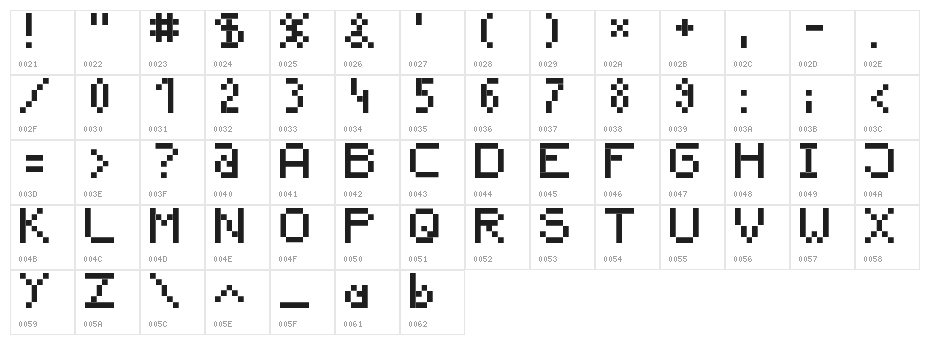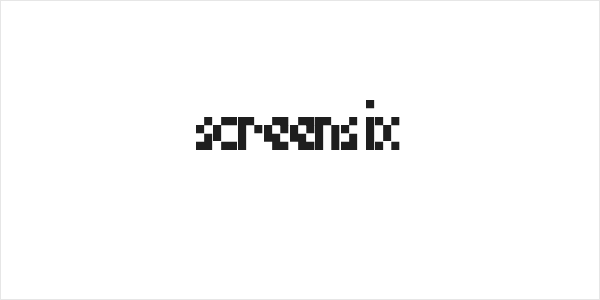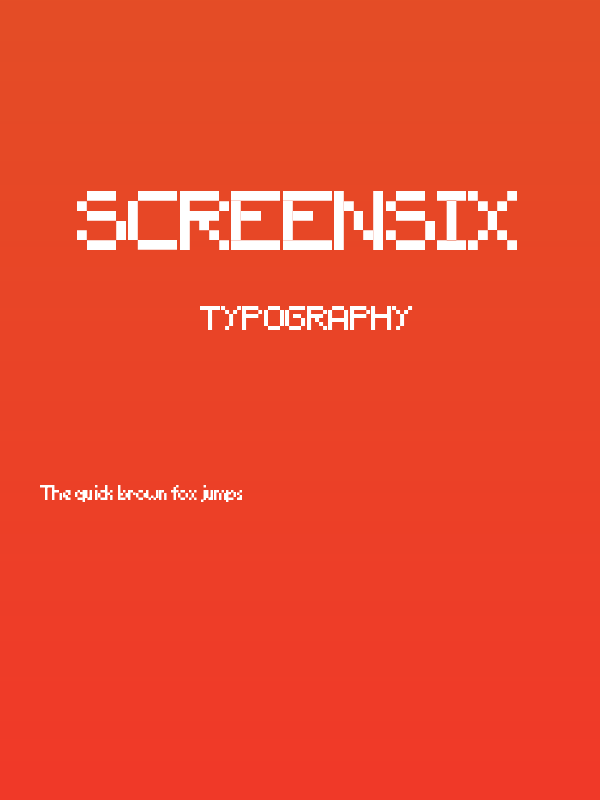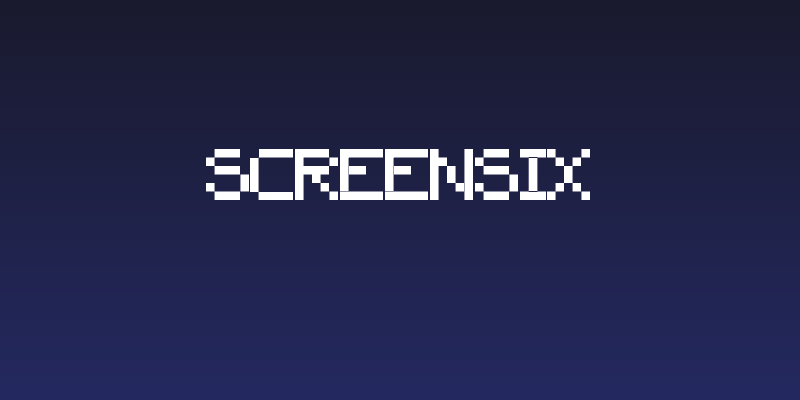
screensix Font
✎ Pixel
| Gesamtstil | Retro, Digital |
| Anwendungsfall | Headlines, Logos, Digital Art |
| Vorgeschlagene Projekte | Ideal for retro video game designs, digital-themed posters, pixel art projects, and any creative work that seeks to evoke nostalgia for early computing aesthetics. |